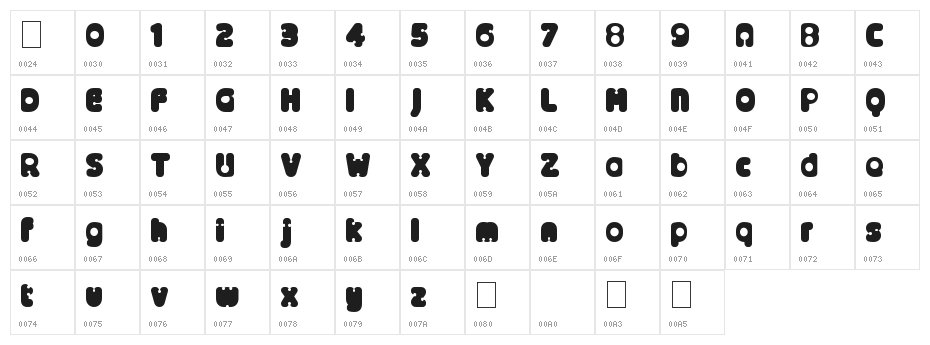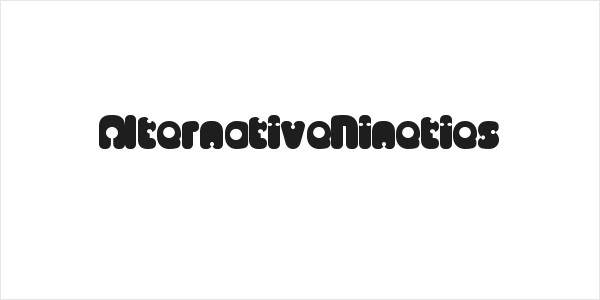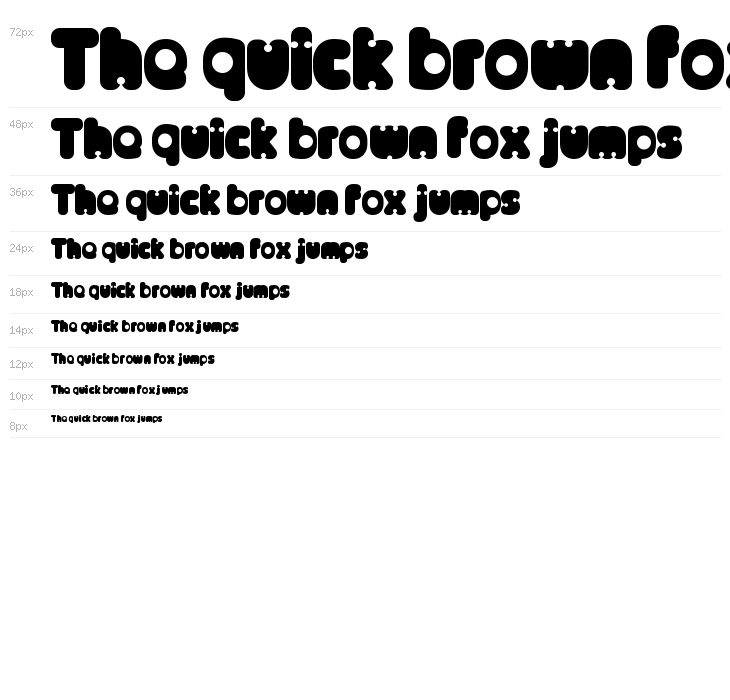
AlternativeNineties Font
| Stile generale | Retro, Playful |
| Progetti proposti | Ideal for posters, album covers, children's books, and branding that seeks a fun and retro vibe. |